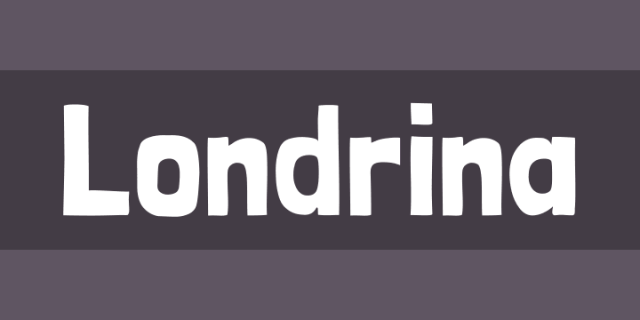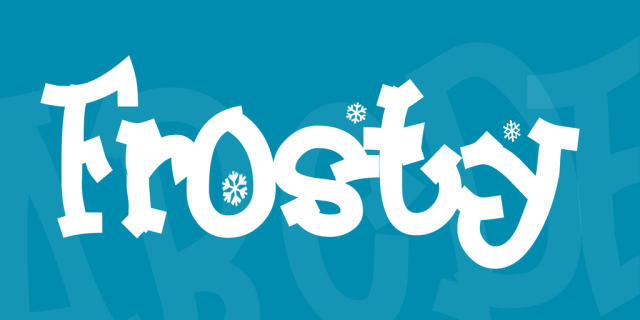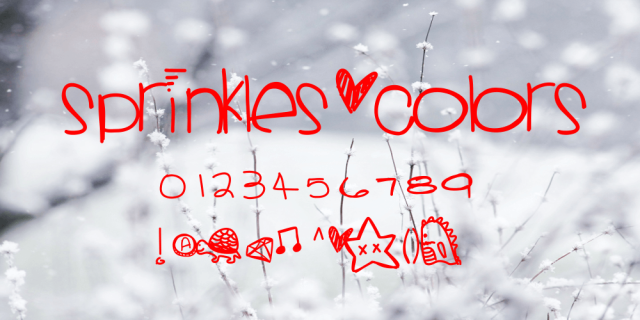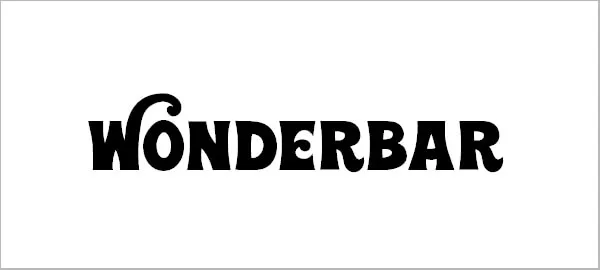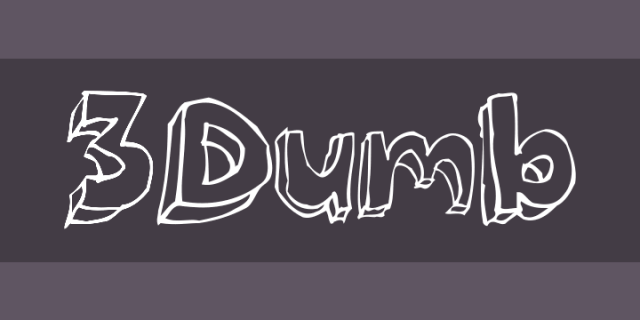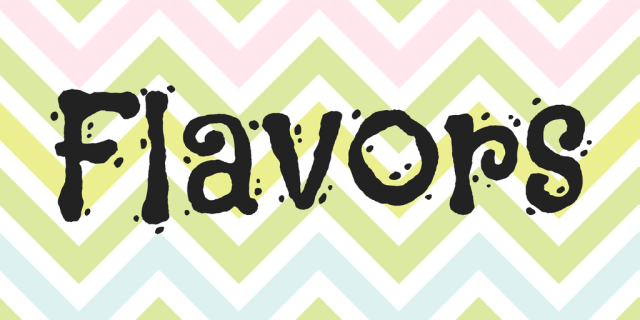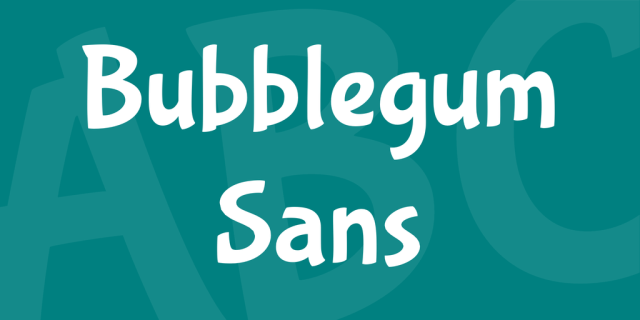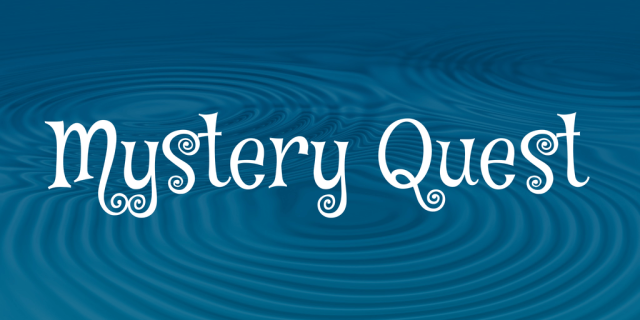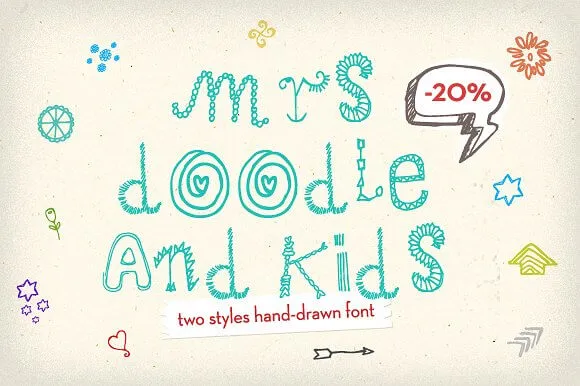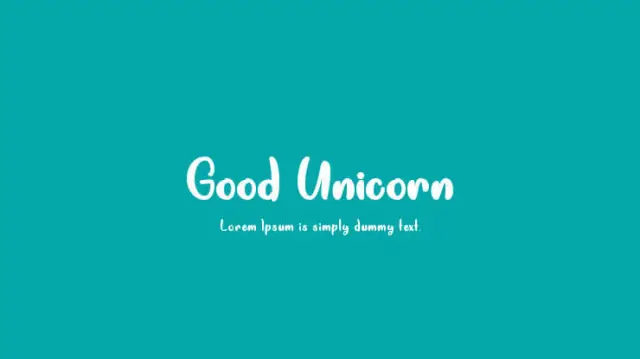
兒童網站和設計項目的 12 種最佳兒童字體
已發表: 2021-11-29兒童字體充滿樂趣,色彩繽紛,充滿樂趣,富有創意,大量令人驚嘆的創意設計讓您可以為兒童網站設計兒童字體。 幸運的是,網絡上有很多孩子仁慈的字體樣式。
在此博客中,我們對 12 種我們最喜愛的兒童字體樣式進行了一些檢查,您可以在下一個設計項目中使用它們。 我們還將討論是什麼讓它們與眾不同以及何時使用它們。
為孩子們設計可以很有趣。 您將有機會在越來越“真正”的冒險中使用通常超出允許範圍的十幾個不尋常的組件。
歸根結底,為一些逐漸隨意的潛在結果敞開心扉的延伸是很高的。 兒童字體樣式是一種快速、非凡的方法,可以讓事物活躍起來。
讓我們來看看它的一些用於設計項目的優秀字體
1. 無泡泡糖:
Bubblegum Sans 並不炫耀,只是讓它更具適應性。 它非常連貫且不引人注目,但同時提供了比您在網絡上看到的典型字體樣式更值得注意的怪異程度。
我們認為這對於數字書籍封面、標題、徽標以及您可以考慮的任何明顯的組件來說都是非凡的。 您甚至可以將 Bubblegum Sans 用作小部分的正文消息,這是兒童網站最好的兒童字體之一。
2. 神秘任務:
這個孩子的字體是免費的,Mistery Quest 是字體樣式的優秀示例之一。 從設計的角度來看,Mistery Quest 簡潔,具有 90 年代風格字體類型的複古集合的外觀和感覺。
每個字母都有錯綜複雜的循環,Mistery Quest 讓您的設計更具吸引力。 與其他字體一樣,此字體也可用於正文、標題和徽標。
3. Mrs. Doodle字體:
從事需要一部分幸福的孩子的項目?
在這一點上獲得這種字體樣式,與其他塗鴉商品一起手工創建的字母,例如花朵、心形、裝飾品、繁榮、螺栓、充氣玩具,這只是冰山一角,它是最適合任何活動的字體樣式適合為兒童網站設計兒童字體項目。
4. 可愛的手繪類型:
真正富有想像力、有趣、可愛的手繪這種可愛手繪類型是一種獨特、大膽的陳述,可用於幻燈片、海報、賀卡、字母、標題等,
5. 冷淡:
免費供個人使用的頂級兒童字體之一,是一款出色、出色的兒童字體。 設計很簡單,就像下雪一樣,霜凍賦予每個字母和字符獨特的形狀。 雪花給這種字體帶來了魅力,這種字體非常適合高度非正式的網站和應用程序。
6. 3啞:
3Dumb 這個名字來源於 3D 設計,大膽、透明,讓您的內容從頁面的其他內容中脫穎而出,最適合任何類型的網站,尤其是兒童網站的兒童字體。
以粗體方式給出標題,標題,可以使用這種字體,因為它完全適合標題標題。
7. Delius 花飾帽:
Delius Swash Caps 想出如何既有趣又傳統。 它是草書的,這在一定程度上會影響可理解性,但是,它可以毫無疑問地使用它來解決您的問題。
鑑於上述情況,我們認為實質性、明確且有效的內容將從這種文本風格中獲益最多。 它甚至可以在逐漸正式的網站上使用,儘管你可能不想偏離它的草書寫作學習很長的路要走。
8. 口味:
Flavours 是一種用於兒童網站的“飛濺”兒童字體。 它看起來被弄髒了,好像是用墨水製成的,並且已經滴了幾滴。 然而,這只是為了突出其迷人的風格,並暗示有“發展”來幫助清晰。
這種字體樣式是標題的絕佳替代品,小說作者可能會傾向於它的樣式。 我們同樣建議臨時指令目的地將從 Flavours 中得到一些利用。
9. 好獨角獸:
閃閃發光,閃閃發光,像星星一樣閃亮,像乳白色的波浪和星系的星星一樣充滿活力和色彩。 Good Unicorn 是最好的,流行和最豐富多彩的兒童字體樣式最適合年輕女孩,孩子。
可以在標題區域、標題欄或關注中心的事件中使用它,有助於為兒童網站製作兒童字體。
10.Sprinklescolors:
Sprinklescolors 看起來就像你在一個偶然的機會中得到的一樣,你讓一個學前的年輕女孩與你保持聯繫,一封信中帶著某些心意。它很有趣,很隨和,而且有很大的吸引力由於所有額外的字符和替代品。
考慮將這種字體樣式用於第一個人的故事或觀點。 如果您的內容可以通過使用表情符號獲利,那麼您就有了業力。 Sprinklescolors 還包括迷人的恐龍、海龜等等。
11. 隆德里納素描:
Londrina Sketch 的風格很難固定。 乍一看,您所看到的那種文本樣式似乎被用作“正式的噴漆”,但結構簡單,非常適合引人注目的標題。
對於這種特定的字體,我們規定要堅持所有頂部和高對比度結構,因此它的出現要多得多。 無論如何,Londrina Sketch 具有足夠的適應性,你也可以從它的小寫變化中獲得很多里程。
12. 奇妙吧:
這是一種有趣且流暢的大寫字體樣式,並且肯定會使這塊糖果有品位。 還包括幾個不同的附加項目和交換,這將有助於製作非單調的結構。
正如您所想像的那樣,徽標將是這裡的天堂。 儘管如此,標題和主要標題也將在 Wonderbar 的駕駛室內。 事實上,非 Web 應用程序特別為這種文本樣式提供了巨大的激勵。
結論!
與以成人為中心的計劃相比,為兒童網站構建兒童字體提供了自己的困難安排。
儘管如此,還有一個難得的機會來度過一段美妙的時光,讓你的創造力盡情發揮,這是越來越“成熟”的項目經常無法承受的。
使用這些說明兒童字體,您可以設計自己的項目,充滿樂趣和創造力。 這些字體將幫助您以更簡單方便的方式設計您的網站。